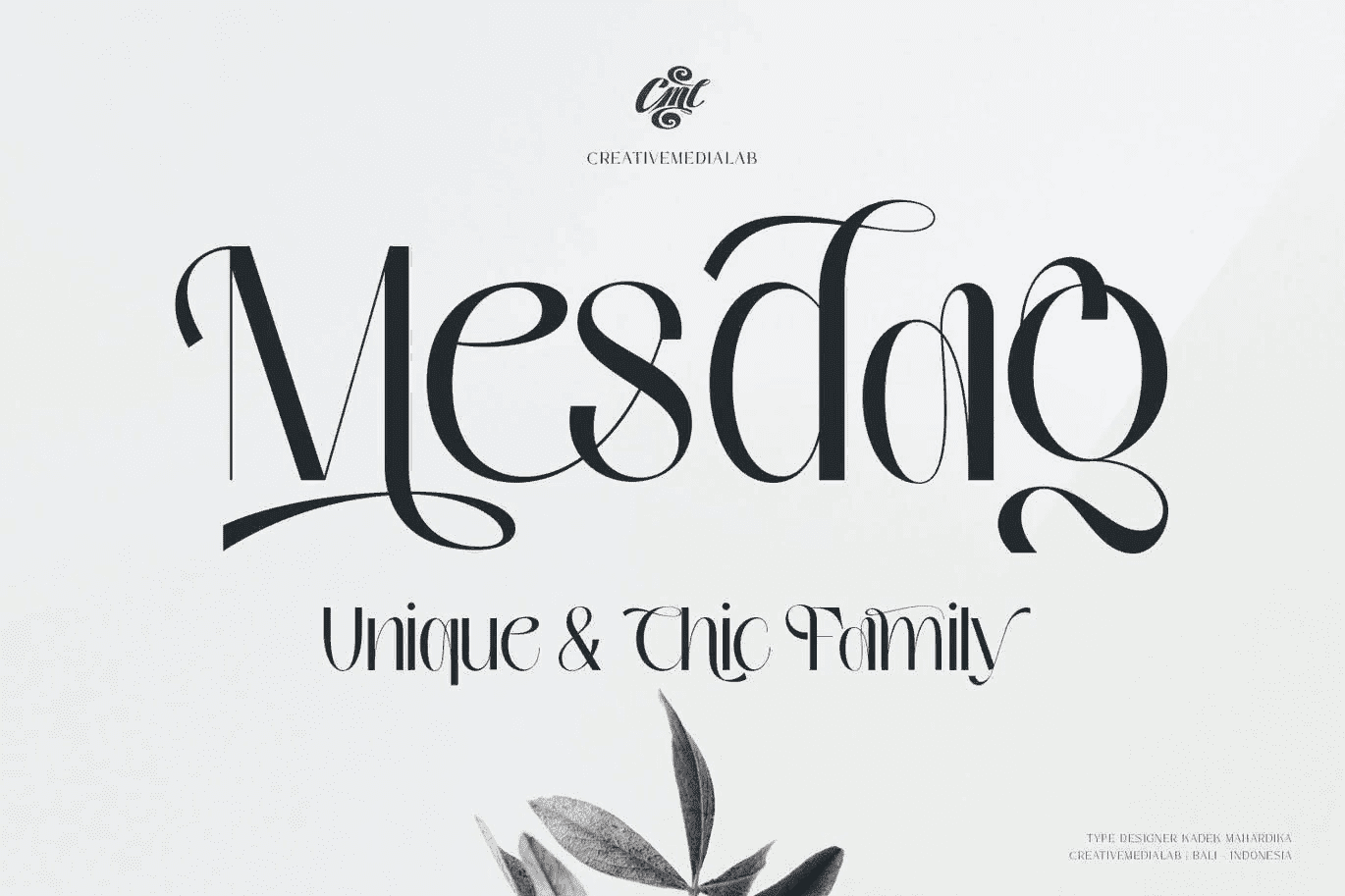
Представляем вам шрифт Mesdag!
Мой эксперимент по объединению шрифтов без засечек, с засечками и рукописных шрифтов, результатом которого стал современный уникальный и шикарный шрифт Mesdag
Это семейство состоит из 9 начертаний и оснащено альтернативными и дискретными лигатурами, которые сохраняют плавные связи между символами. Кроме того, в семейство входит стиль Variable, а также многоязычная поддержка, цифры и символы валют.
Это семейство подходит для использования во многих формах дизайна, например, журналы, заголовки, дисплеи, открытки, логотипы, DIY проекты, пригласительные открытки, цитаты, винтажный дизайн, старая классика, 60-е, 70-е, 80-е годы, свадебные проекты и многое другое.